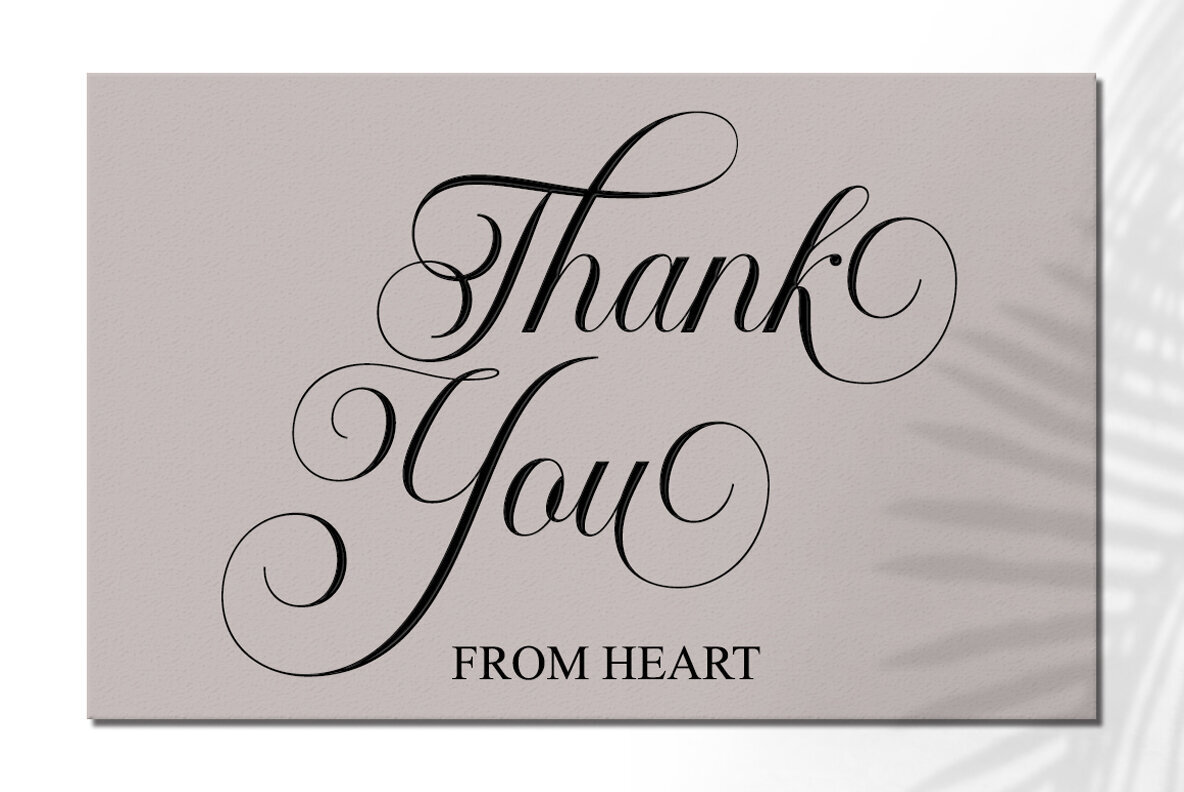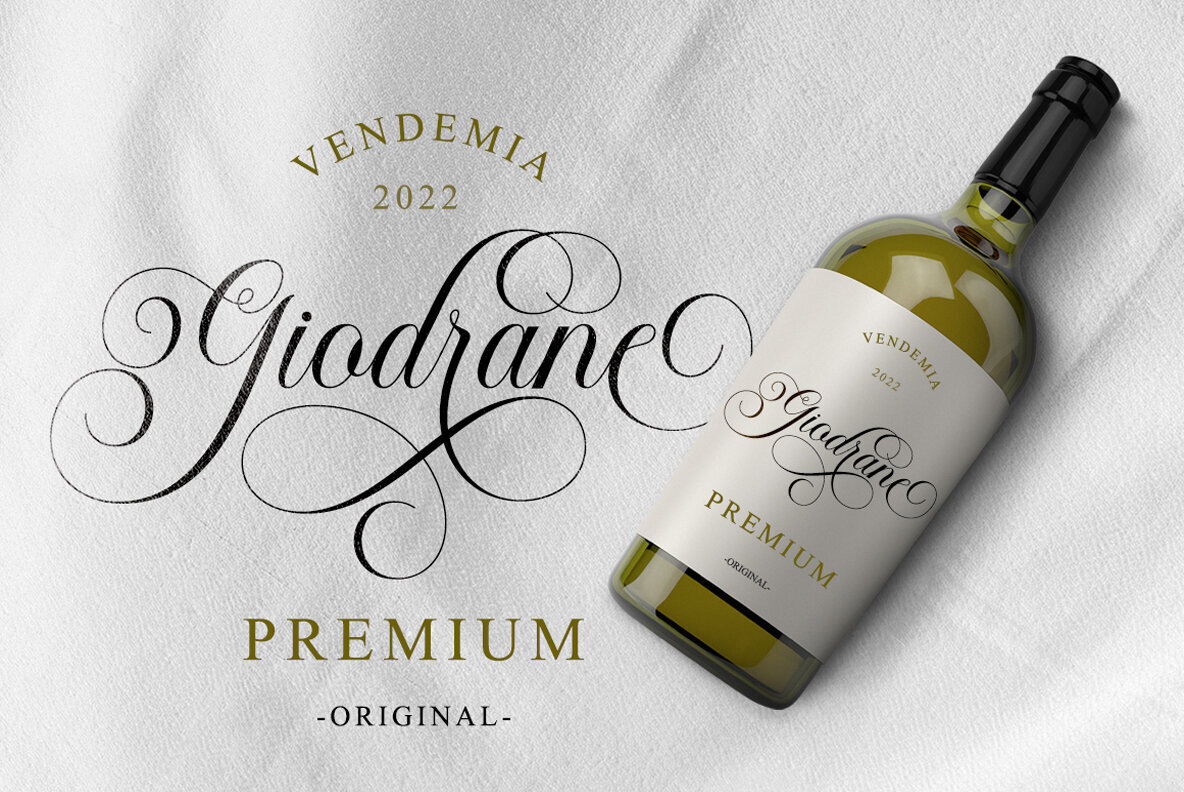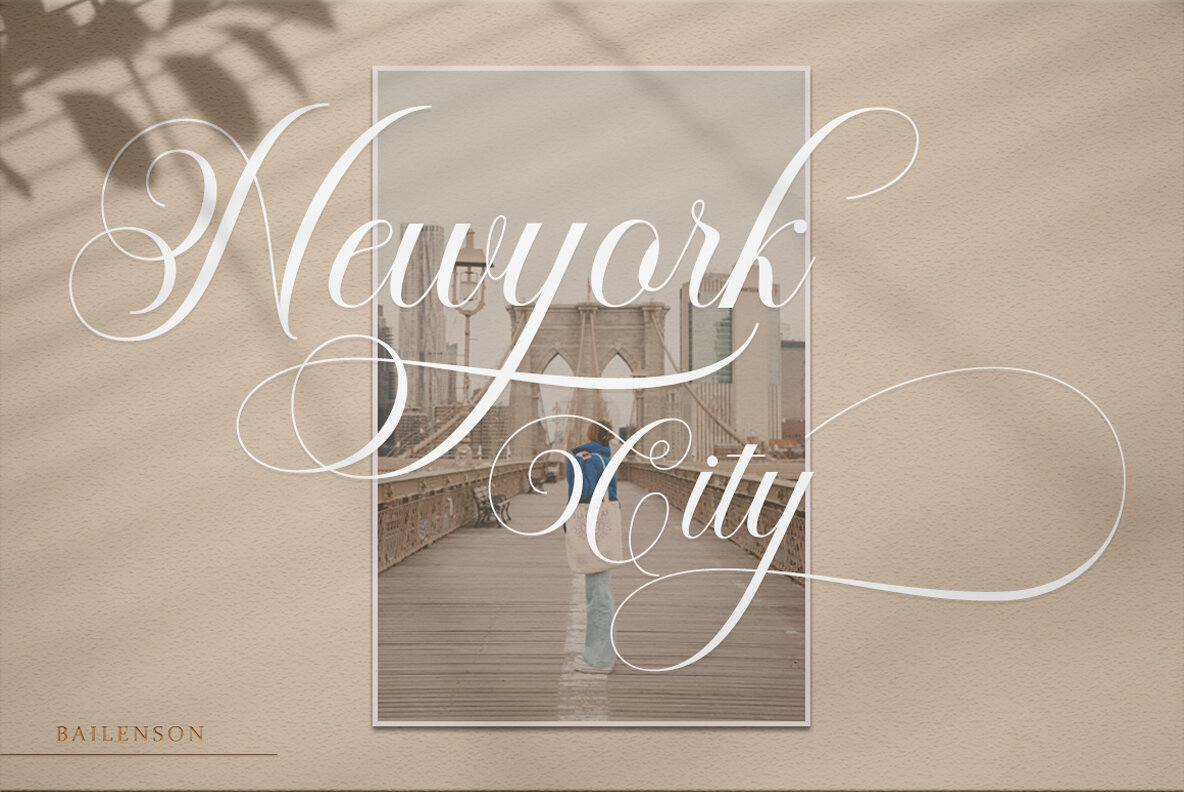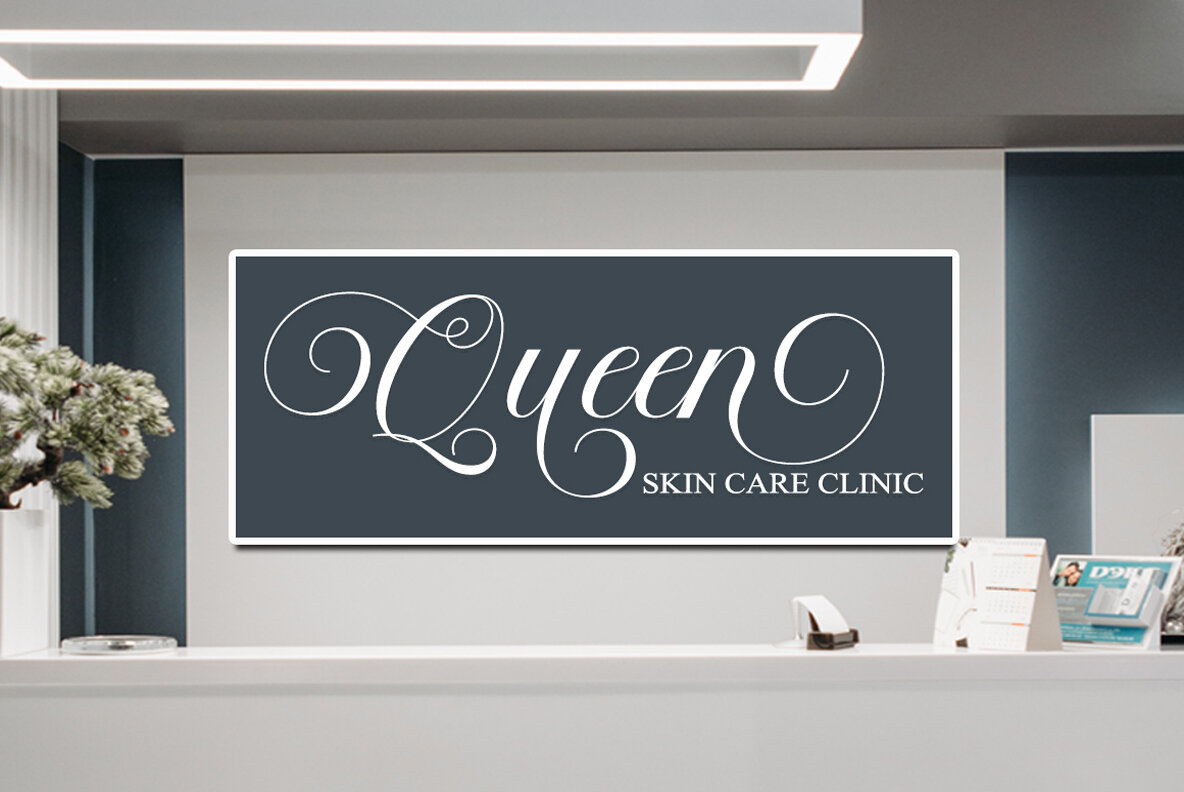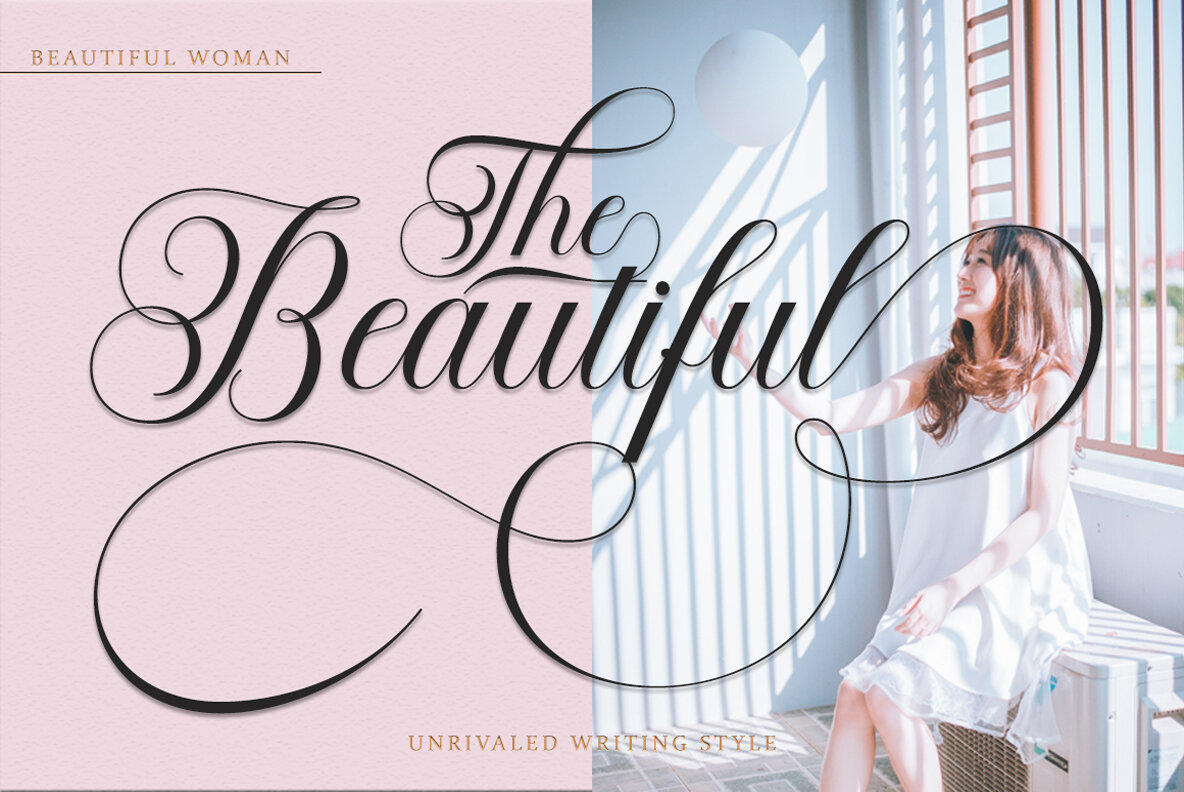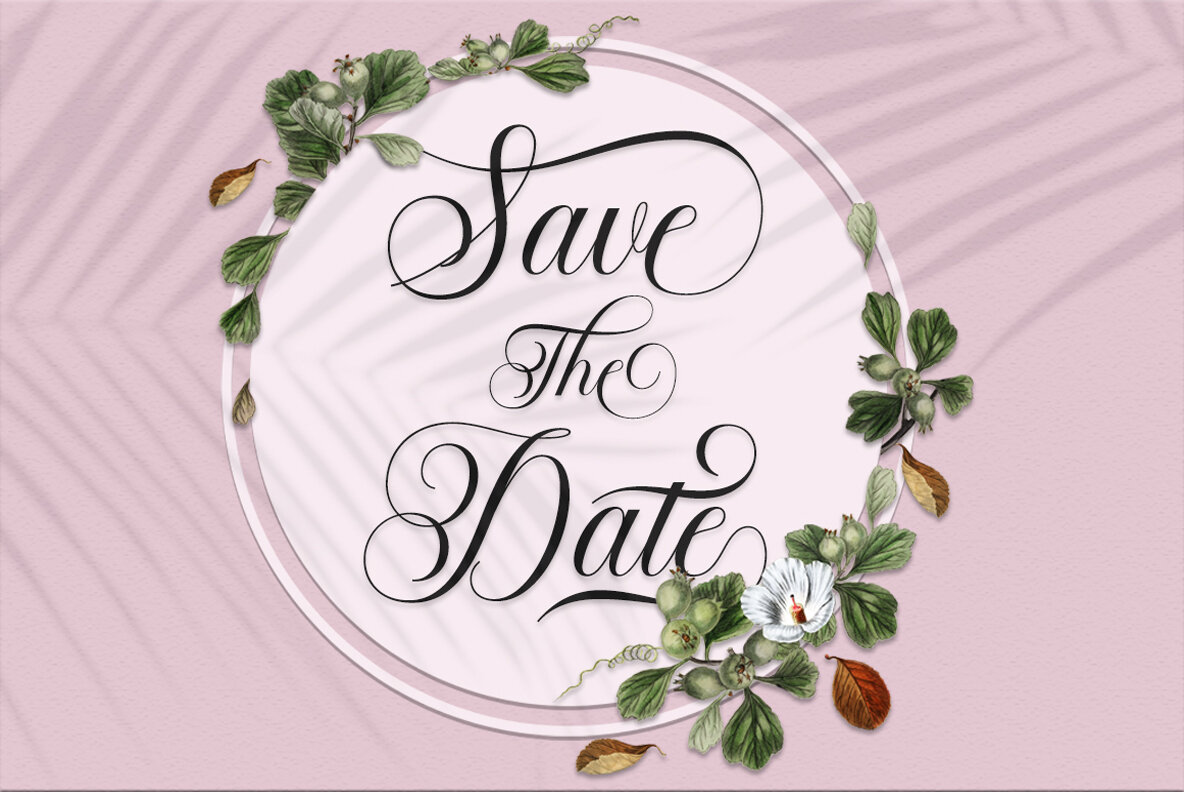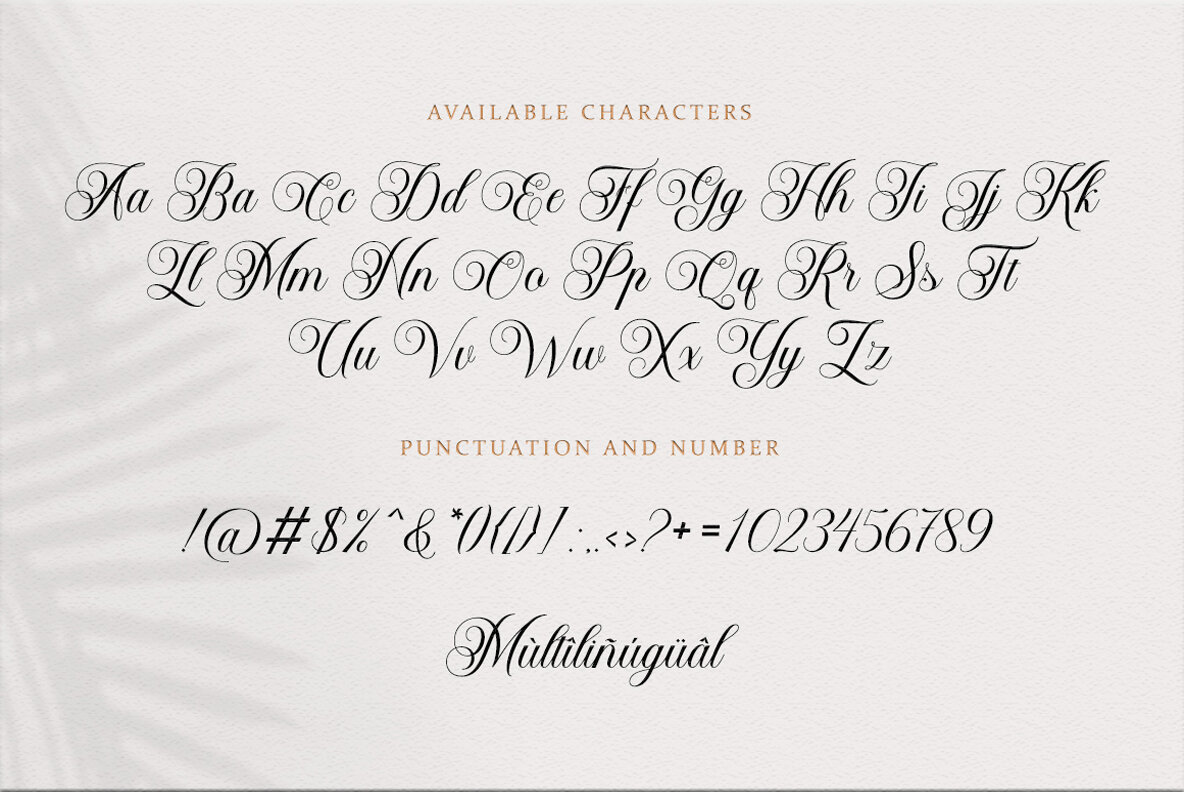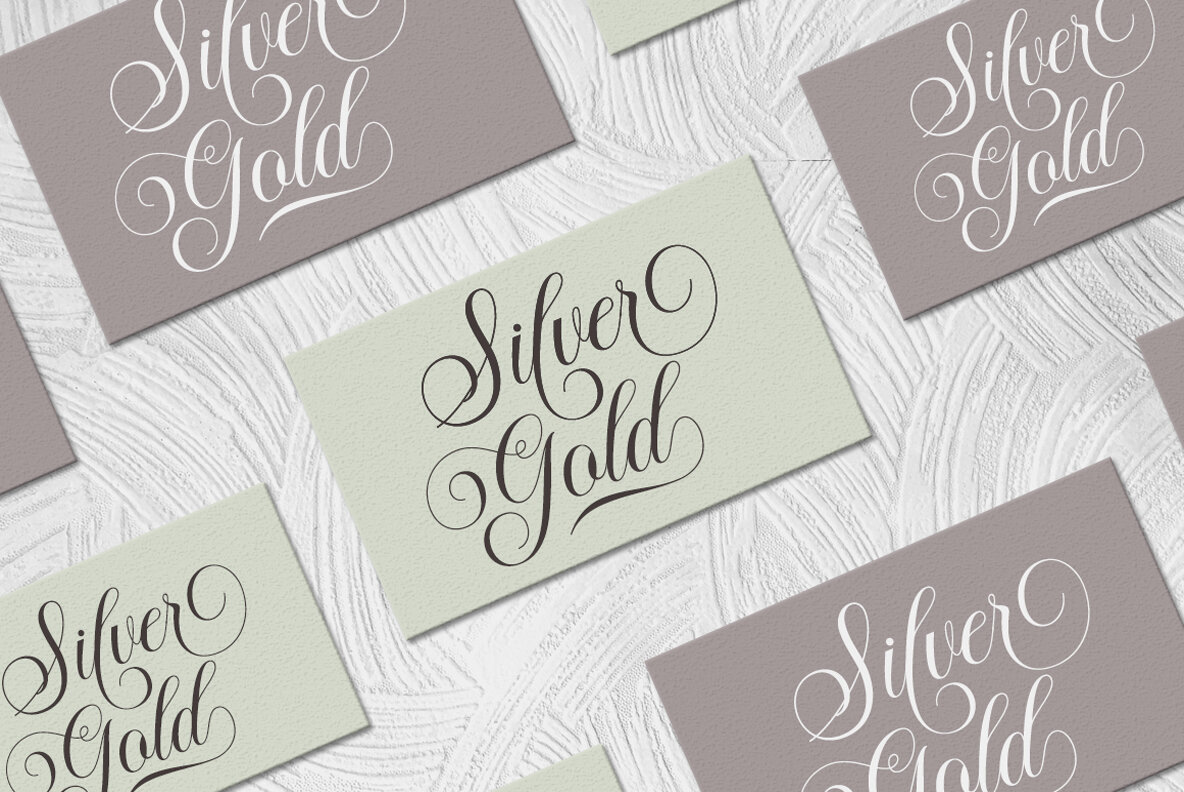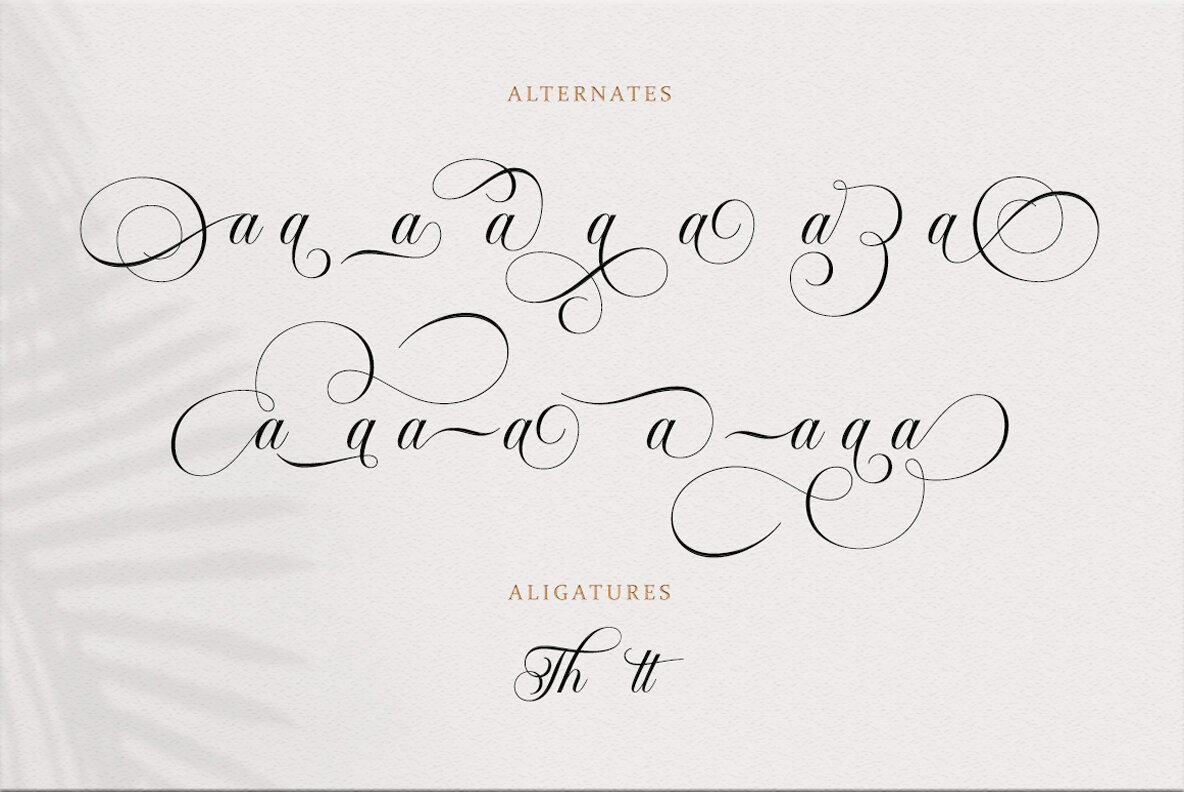
Bailenson Font
Bailenson Regular
Bailenson Italic
Memperkenalkan font kaligrafi Bailenson yang mencolok, dibuat dengan penuh kasih oleh desainer mahir, Pista Mova. Dipenuhi dengan pesona vintage yang mengingatkan pada tulisan tangan wanita Italia klasik dan manuskrip sejarah, daya tarik Bailenson terletak pada perpaduan sempurna antara tradisi dan kecanggihan. Dibuat dengan tekun, font luar biasa ini menawarkan harmoni yang seimbang sehingga menjadikannya pilihan untuk berbagai usaha desain. Dari mendesain suvenir pernikahan yang menarik, sampul buku yang menawan hingga materi pemasaran yang beragam, Bailenson menanamkan keanggunan dan profesionalisme dalam setiap desain. Tidak mengherankan jika desainer grafis dan perusahaan pemasaran menemukan Bailenson sebagai alat yang dapat dipercaya untuk mengkomunikasikan kemewahan, kelas, dan keistimewaan. Nikmati kemegahan font Bailenson Pista Mova, di mana gaya klasik berpadu dengan keanggunan dan fungsionalitas.Memperkenalkan Font Kaligrafi Bailenson: Klasik Berpadu dengan Keanggunan untuk Desain Grafis